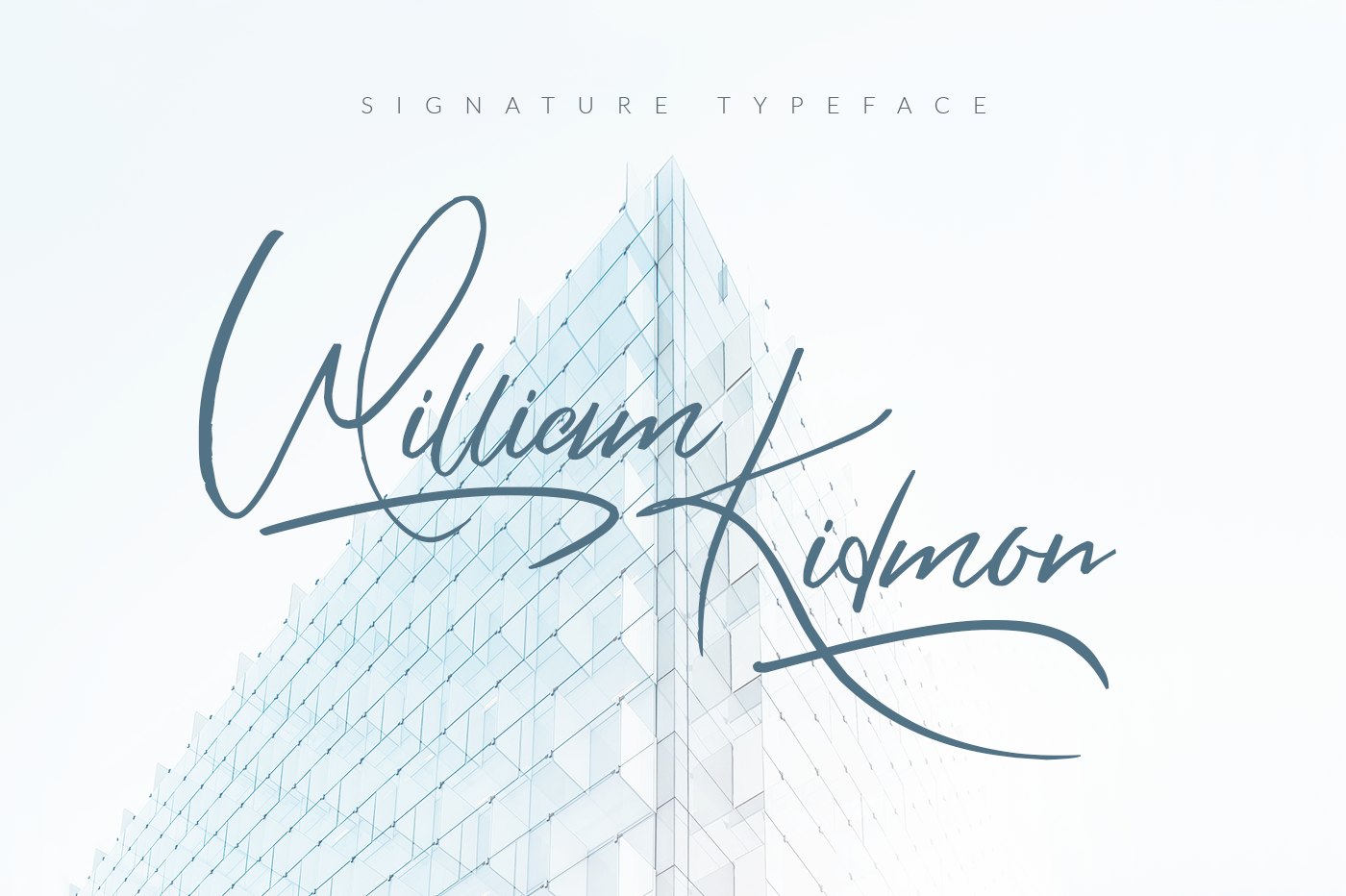
William Kidmon Script Font – Download Grátis
William Kidmon Script Font é uma fonte escrita a mão que oferece um encanto natural e envolvente para qualquer projeto editorial ou design digital. Ideal tanto para textos como para cenas de texto, essa fonte desliza enquanto você escreve, com sua trilha que flui à medida que você digita. Assim que olhamos nos nossos próprios trabalhos digitais, William Kidmon Script Font parece um registro autêntico e artesanal da maneira como a escrita se desenvolve no papel. Desenvolvida por Hamilton, essa fonte é um verdadeiro ato de arte, com linhas que parecem extrema mesmo antes de você finalmente digitá-las. Mas não se deixe enganar pela aparência rígida das linhas: a William Kidmon Script Font é incrivelmente legível e prazerosa para ler, sua natureza fluida garantindo que seu texto sempre seja perfeitamente apresentável. Sem dúvida uma fonte única em seu gênero, William Kidmon Script Font não apenas impressionará seus clientes ou leitores com a sua beleza, mas também os envolverá na experiência de desfrutar da experiência de ler ou escrever em tal fonte.